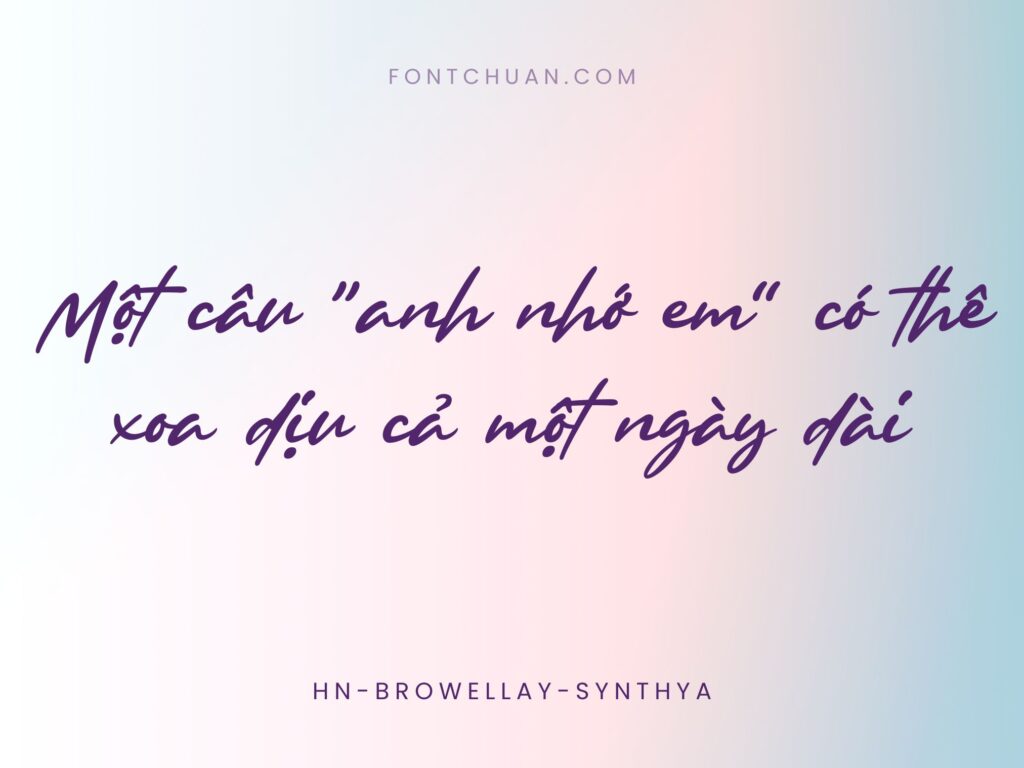
Font Browellay Synthya Việt Hóa
Browellay Synthya là một phông chữ chữ ký hiện đại, được thiết kế bởi Arterfak Project. Phông chữ này mang phong cách viết tay tinh tế, phù hợp cho các dự án như logo, thương hiệu, thiết kế bao bì, thiệp mời và nhiều ứng dụng sáng tạo khác. Phiên bản HN Browellay Synthya đã được Việt hóa bởi Huy Nam, hỗ trợ đầy đủ các ký tự tiếng Việt, giúp người dùng Việt Nam dễ dàng tích hợp vào các thiết kế địa phương. Việc Việt hóa này nhằm đáp ứng nhu cầu của cộng đồng thiết kế và giúp áp dụng vào các dự án thực tế.
Về đặc điểm thiết kế, Browellay Synthya có các đường nét mềm mại và uyển chuyển, tạo cảm giác như chữ viết tay tự nhiên. Phông chữ này phù hợp cho các ứng dụng như thiệp mời, tiêu đề, bao bì sản phẩm và các dự án sáng tạo khác. Đồng thời, Browellay Synthya cũng có thể được sử dụng như một Font chữ thiệp cưới, giúp các nhà thiết kế tạo ra những tấm thiệp cưới lãng mạn, tinh tế và trang nhã. Ngoài ra, Browellay Synthya cũng có thể sử dụng như một Font chữ Giáng Sinh để trang trí thiệp, poster hay banner mùa lễ hội, mang đến không khí ấm áp, vui tươi và sinh động cho các sản phẩm thiết kế.